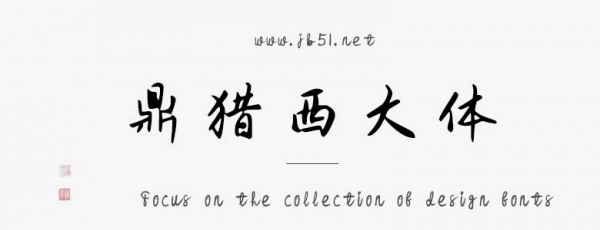
鼎獵西大體由鼎獵字庫出品的藝術字體,以作者母校簡稱命名,追憶恰同學少年,具有很好的視覺感,適合應用于藝術設計、平面宣傳設計、網(wǎng)頁設計,書法字帖等領域。有需要的朋友快來本站下載使用吧。
字體介紹
鼎獵西大體,是一款自由的手寫行楷。鼎獵西大體以作者母校簡稱命名,追憶恰同學少年。鼎獵西大體并不完美,就像是我們總有些遺憾的青蔥校園歲月,也像我們總有些力所不逮的煙火生活。可,歲月悠悠,學海茫茫,人海茫茫。我們依舊載滿美好的回憶與憧憬。鼎獵西大體排版時自由肆意,版式灑脫無拘,適合美食餐飲、文化藝術展覽、企業(yè)文化,以及封面雜志海報、餐飲茶飲、美妝護膚等各個行業(yè)。
考慮到字體應盡可能滿足各類型的需求,鼎獵西大體以簡體中文漢字編碼國家標準(GB2312編碼)為標準,共計設計了多達7415個字符,其中漢字6769個。可以滿足絕大部分印刷設計等要求。